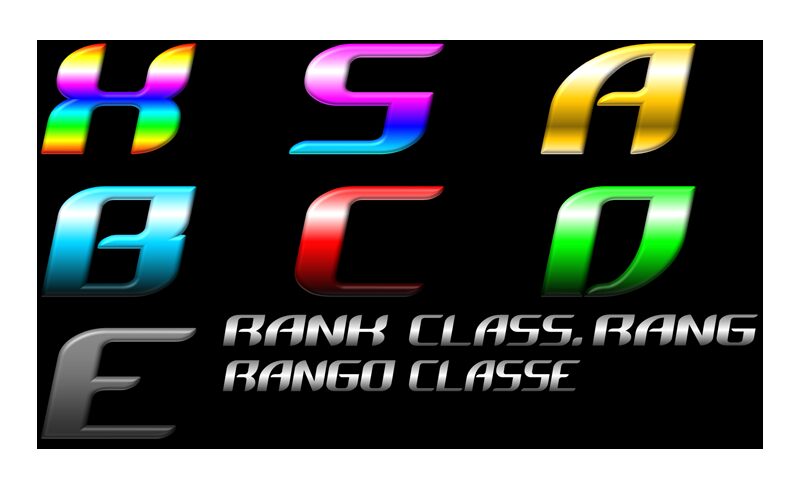
Ukážka písma Zero G Italic
Zero G Italic je bezplatné techno písmo typu display s elegantným, takmer futuristickým sklonom. Písmená pôsobia rýchlo a aerodynamicky, vytvorené zo širokých zaoblených ťahov a hranatých výrezov, ktoré slovám dodávajú plynulý, kĺzavý rytmus namiesto ostrého mechanického dojmu.
Hodí sa pre sci-fi branding, názvy hier, titulky na plagáty, logá v štýle rozhraní či obaly hudobných albumov, kde bezplatné písmo potrebuje dynamiku, no bez chaosu. Keďže si tvary zachovávajú hladkosť a prepojenosť, dobre funguje aj pri krátkych titulkoch a monogramoch, ktoré si vyžadujú kompaktný, technický vzhľad.
Prezentácia a vizuálna ukážka písma Zero G Italic